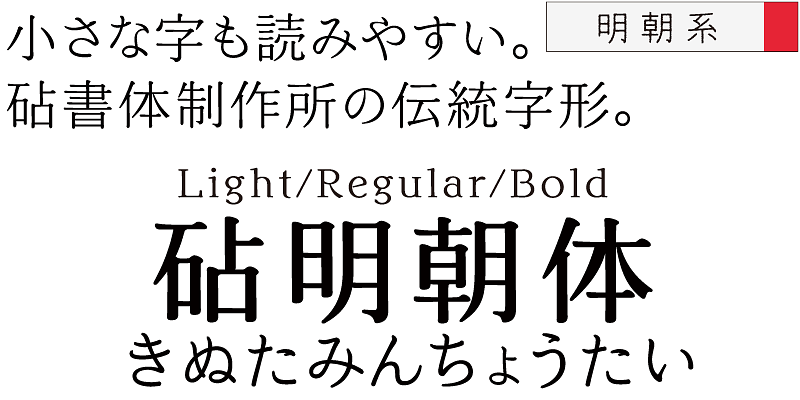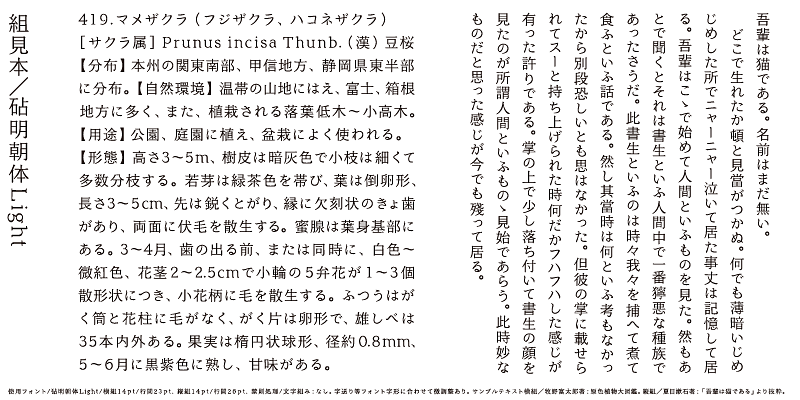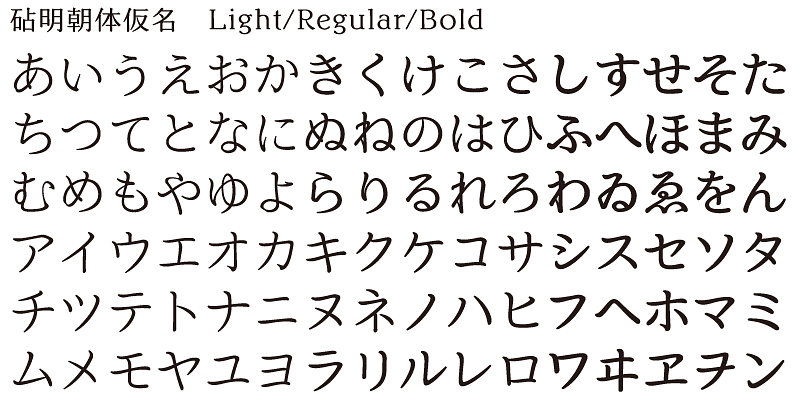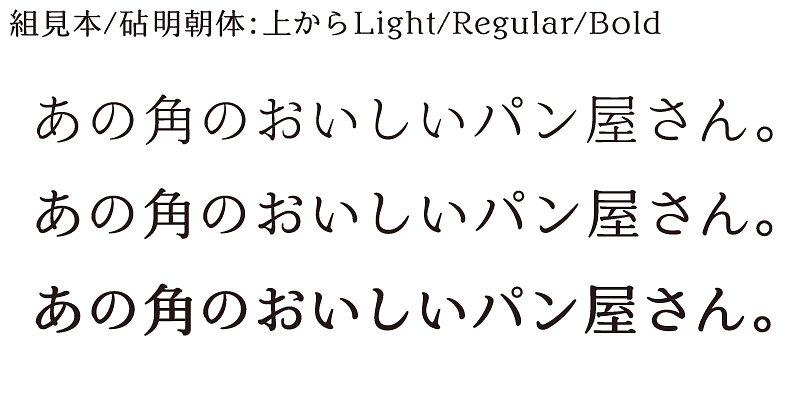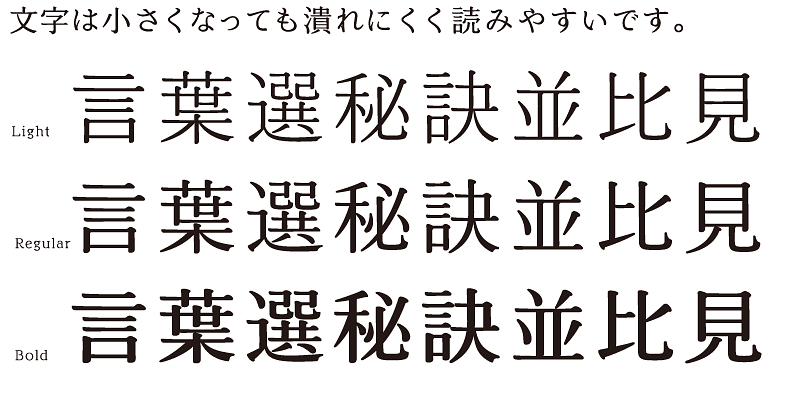
Le dessin des kanji, des kana, des caractères latins et des nombres de Kinuta Minchotai se fonde sur deux concepts : « élégance » et « ma (espace) ». Les caractères kanji qui n’utilisent pas de lignes droites ont un aspect lisse et élégant, en particulier pour les tailles de caractères plus grandes. Les caractères latins intègrent des éléments des caractères kanji, créant une collaboration sans précédent entre l’Occident et l’Orient. Les yeux du lecteur parcourront facilement le texte en Kinuta Minchotai. Trois graisses sont disponibles.
L’une des particularités de la langue japonaise réside dans son utilisation de caractères syllabiques, les kana. Ceux-ci ont été inventés au Japon pour représenter les sons du japonais et traduire les textes importés de Chine. Ce sont eux qui permettent de créer des mots et des expressions japonais à partir de caractères idéographiques (kanji ou caractères chinois). Même s’ils peuvent présenter des ambiguïtés, ces mots et expressions témoignent de la chaleur et de la douceur de la vie des habitants de ce petit pays densément peuplé qu’est le Japon.
Kinuta Font Factory estime que les kana sont à l’origine même de l’écriture du japonais, et nous pensons que les améliorer peut contribuer à donner encore plus de charme aux textes japonais. En moyenne, 60 % des écrits japonais sont consitués de kana. Changer la forme de ces caractères peut donc transformer l’aspect visuel de ces textes. Les possibilités d’expression typographique utilisant des kana simples, dynamiques et curvilignes sont vastes, et la richesse de la langue japonaise écrite repose sur ces caractères. C’est la raison pour laquelle Kinuta Font Factory propose un large éventail de variantes de polices kana.